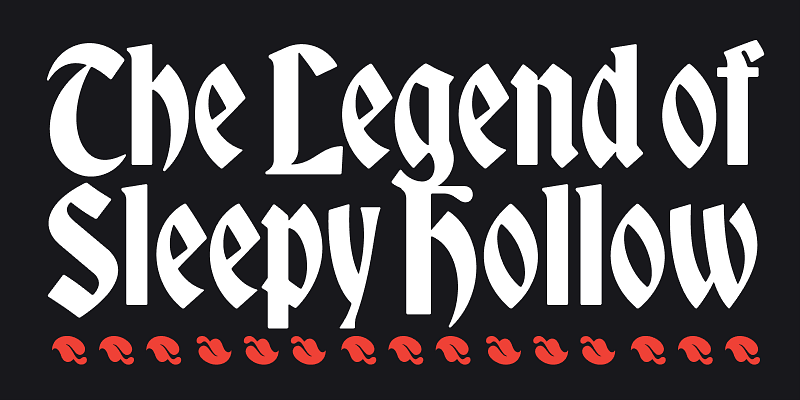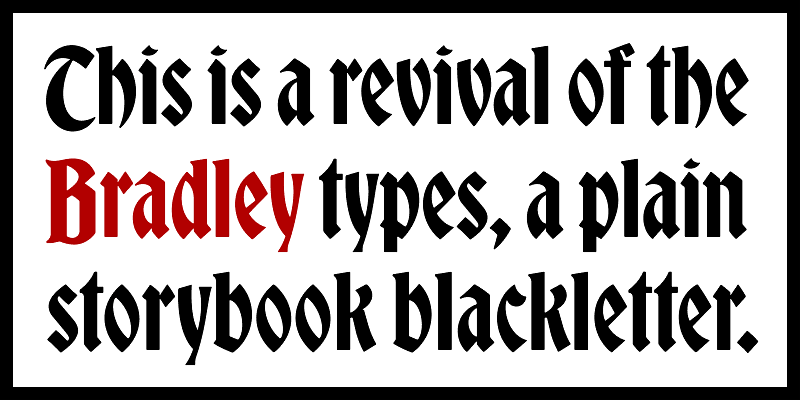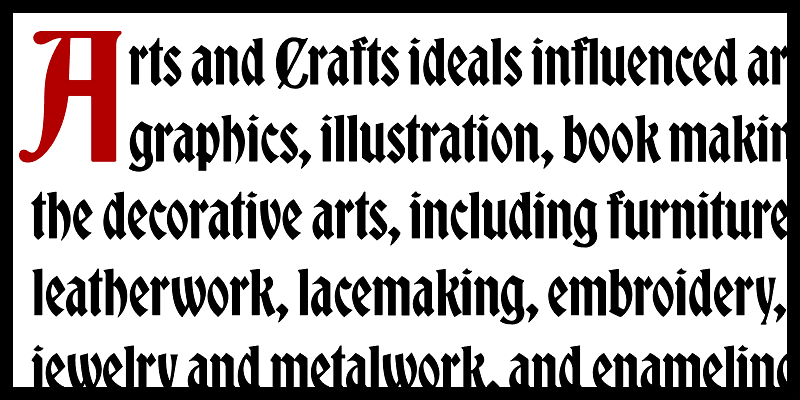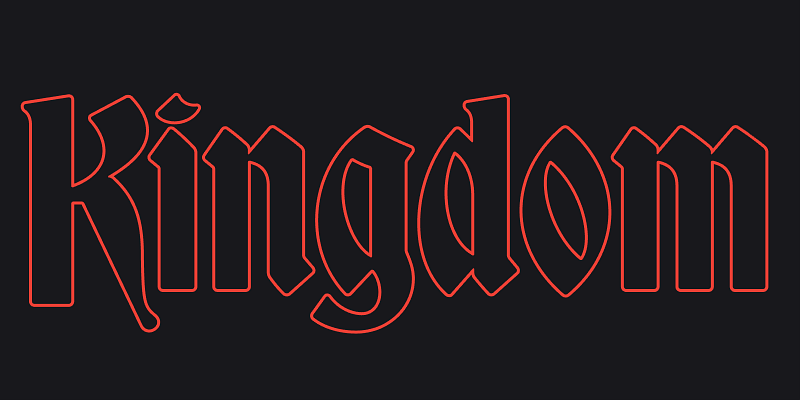
「Bradley DJR」は、1895 年に American Type Founders が発表した「Bradley」のリバイバル版の書体です。ベースとなったのは、『The Inland Printer』誌のクリスマス版を飾った Will H. Bradley の表紙であり、多くの記録によると、Hermann Ihlenburg が書体デザインを完成させました。単純化されたフォルムはブラックレターに馴染みのない読者にも親しみやすく、今回のリバイバル版ではその柔らかさ、大文字の下降、独特の絵本的な性格を残そうと試みられています。